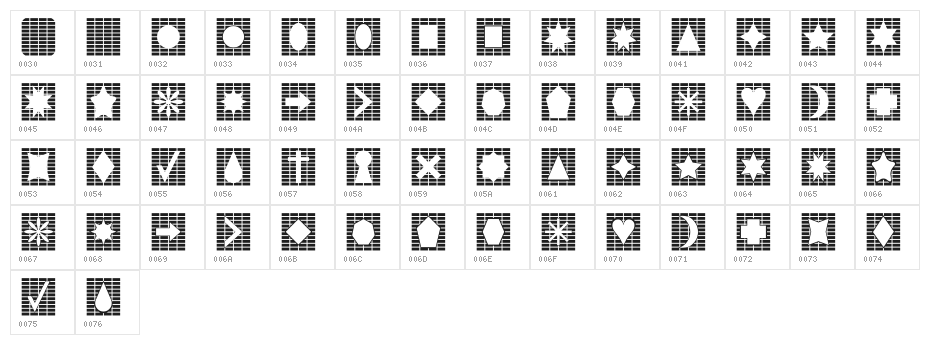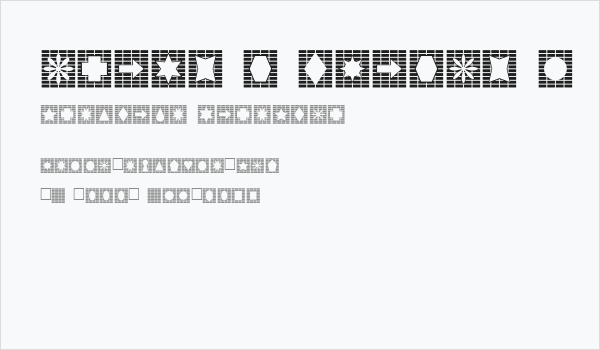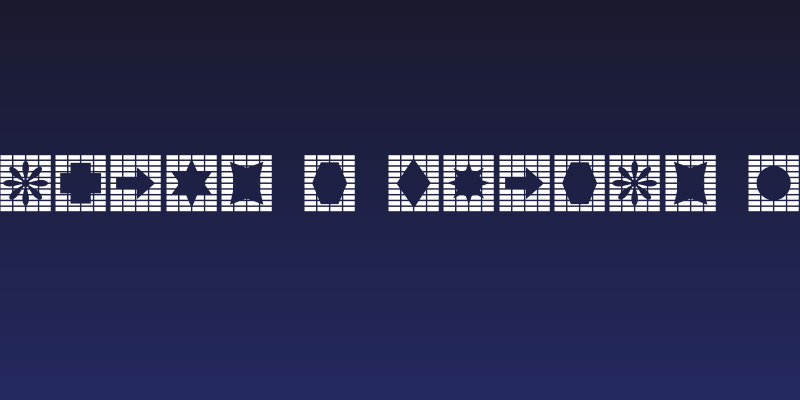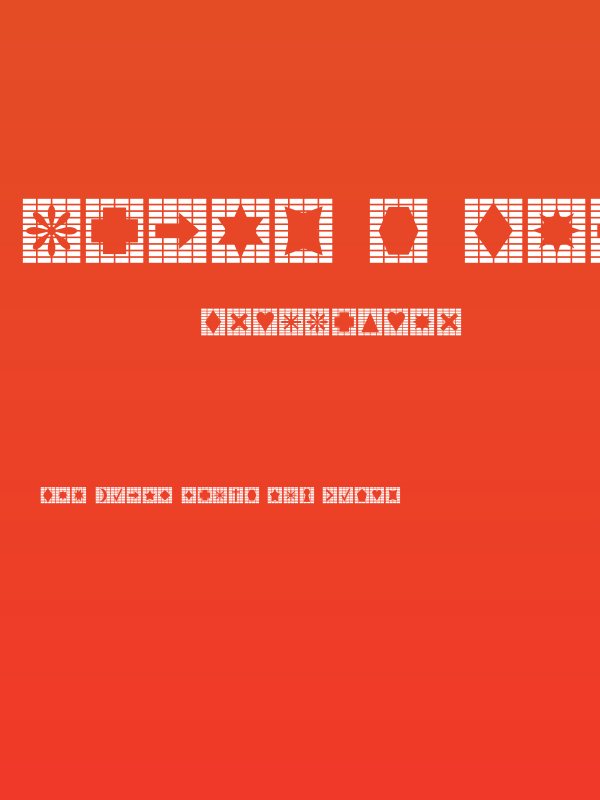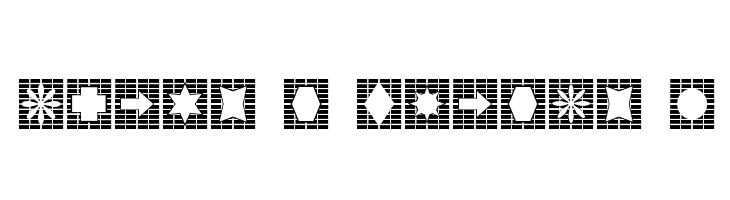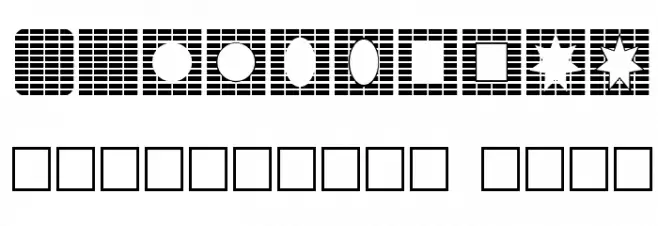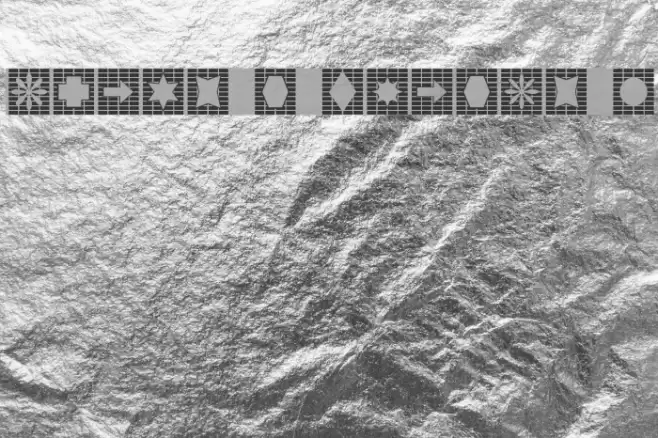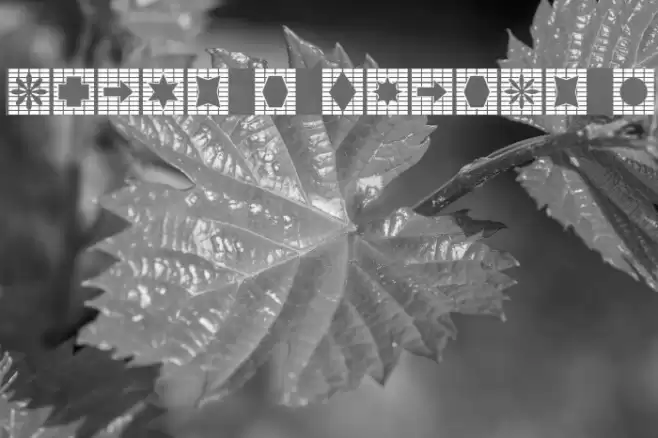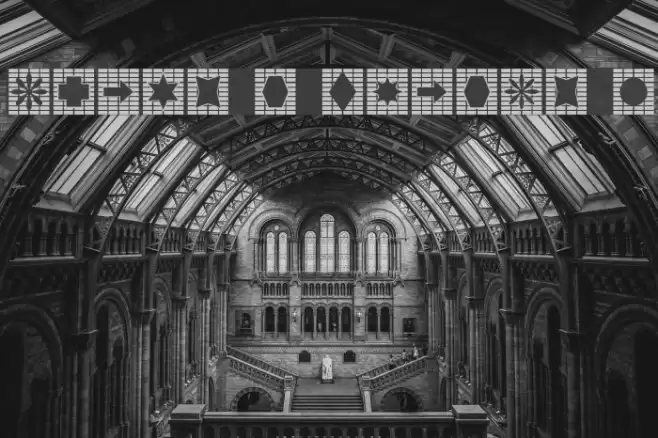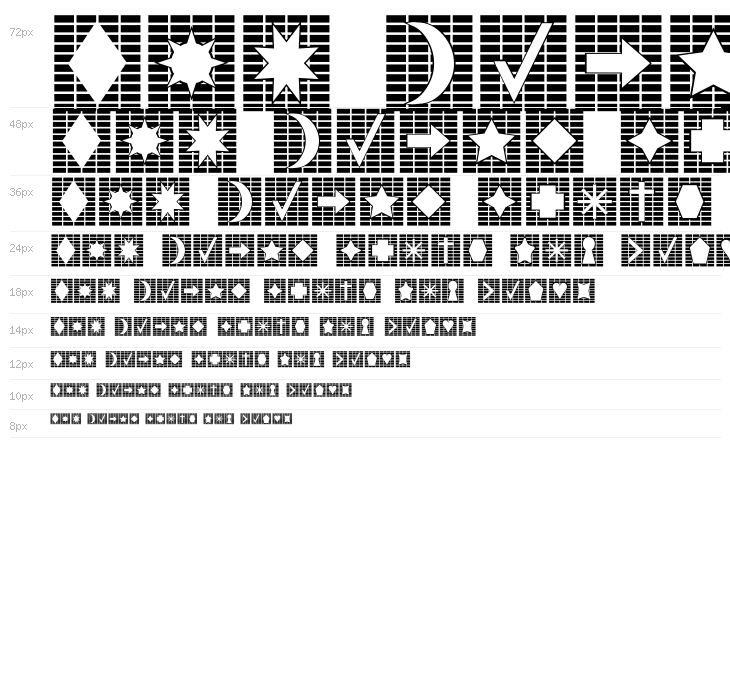
Grids n Things 2 Font
| Caso d'uso | Logos, Decorative elements, Educational materials |
| Progetti proposti | Ideal for creative design projects, pattern creation, educational tools, or decorative elements in digital and print media. |